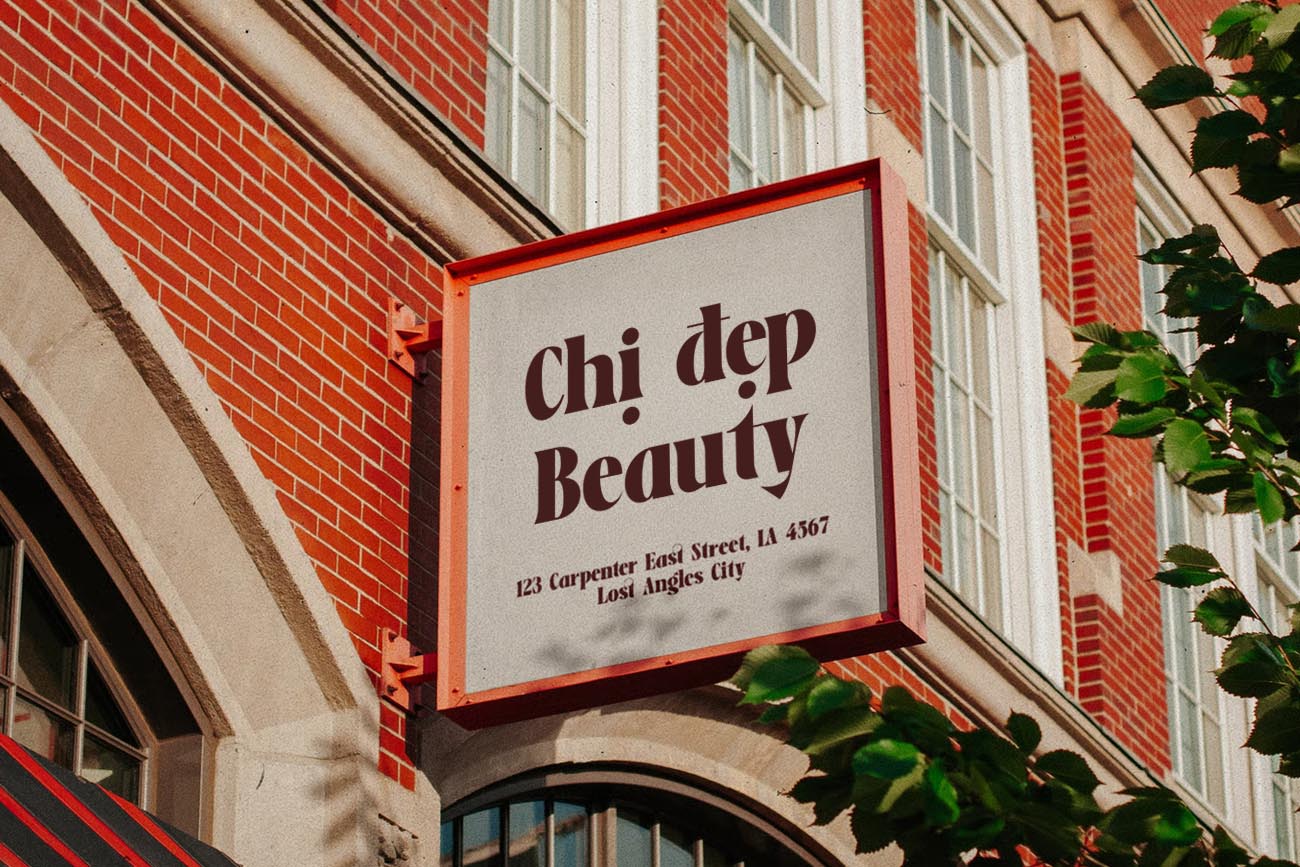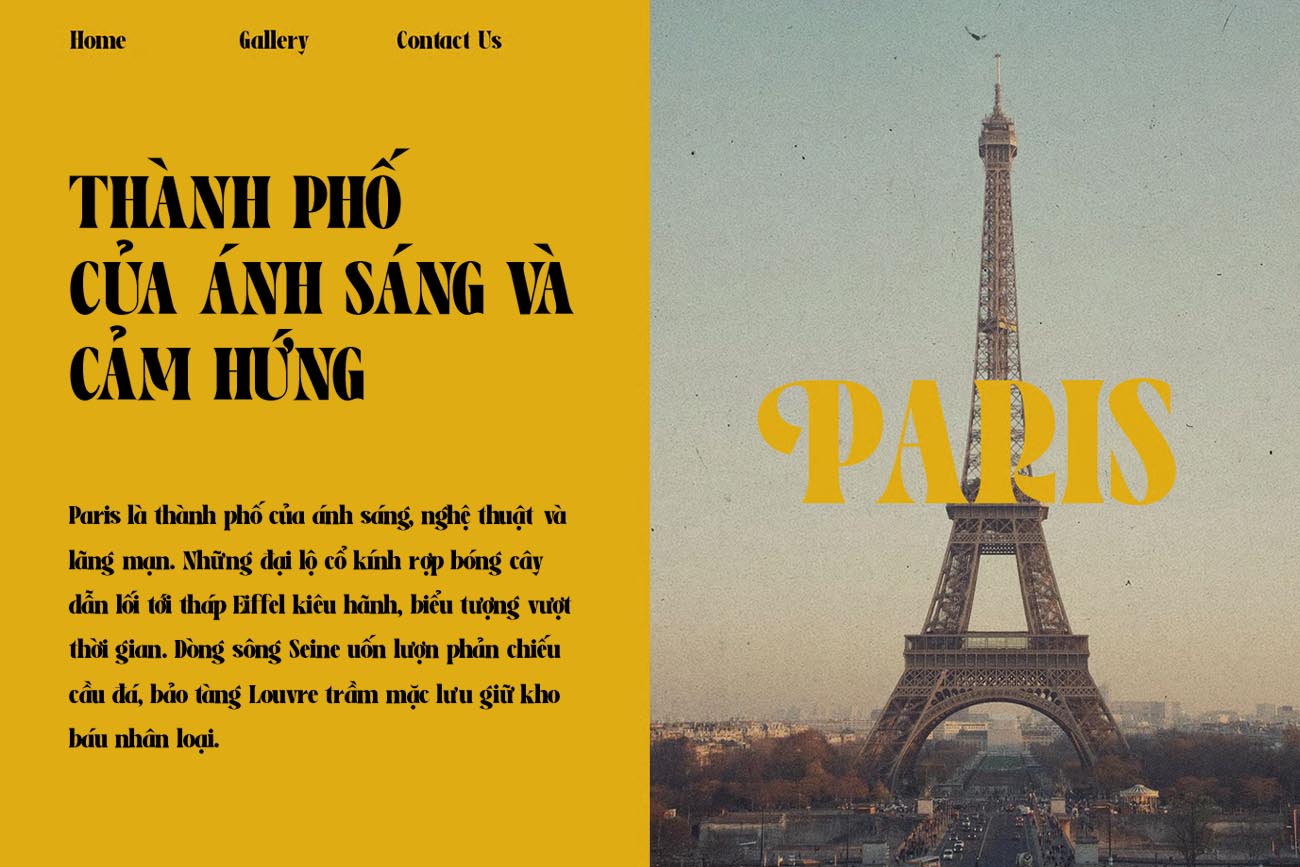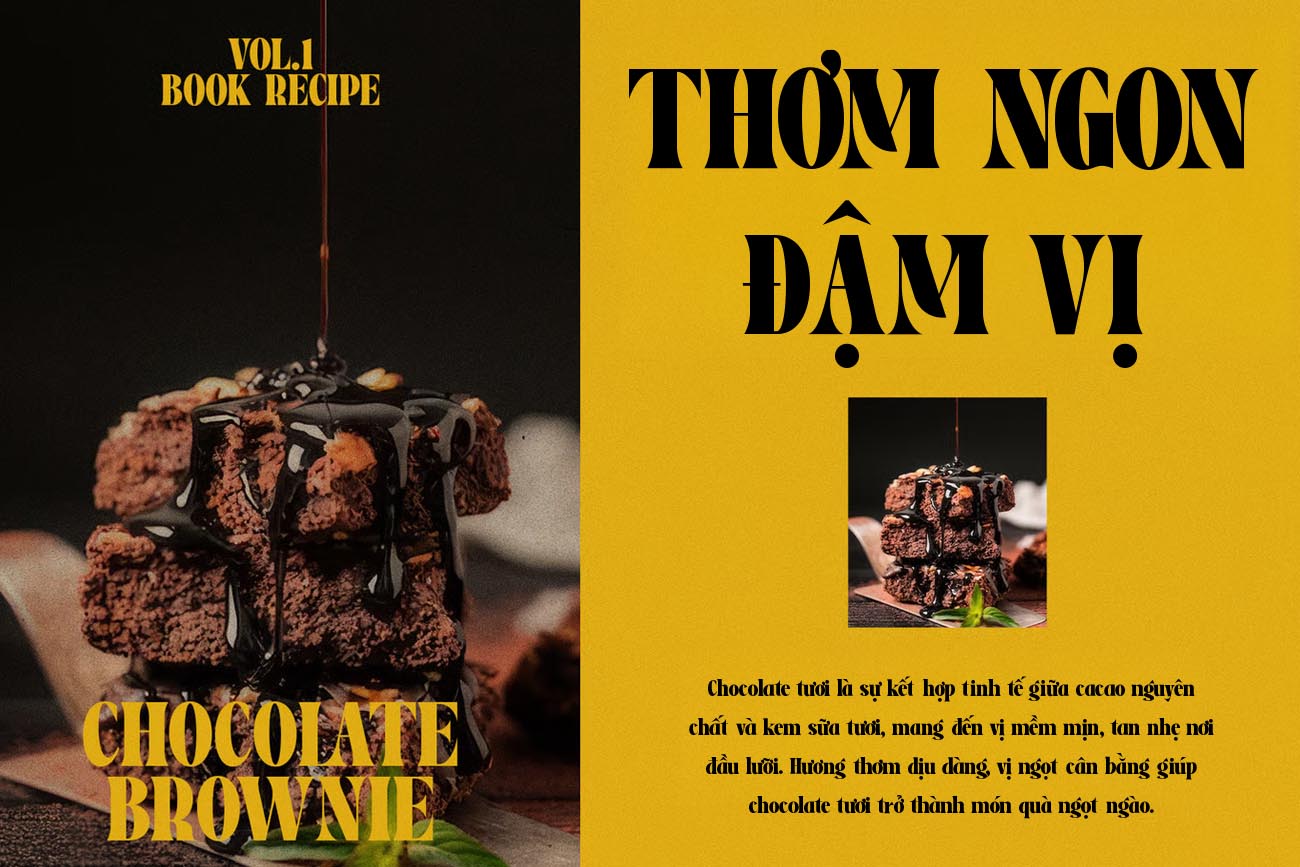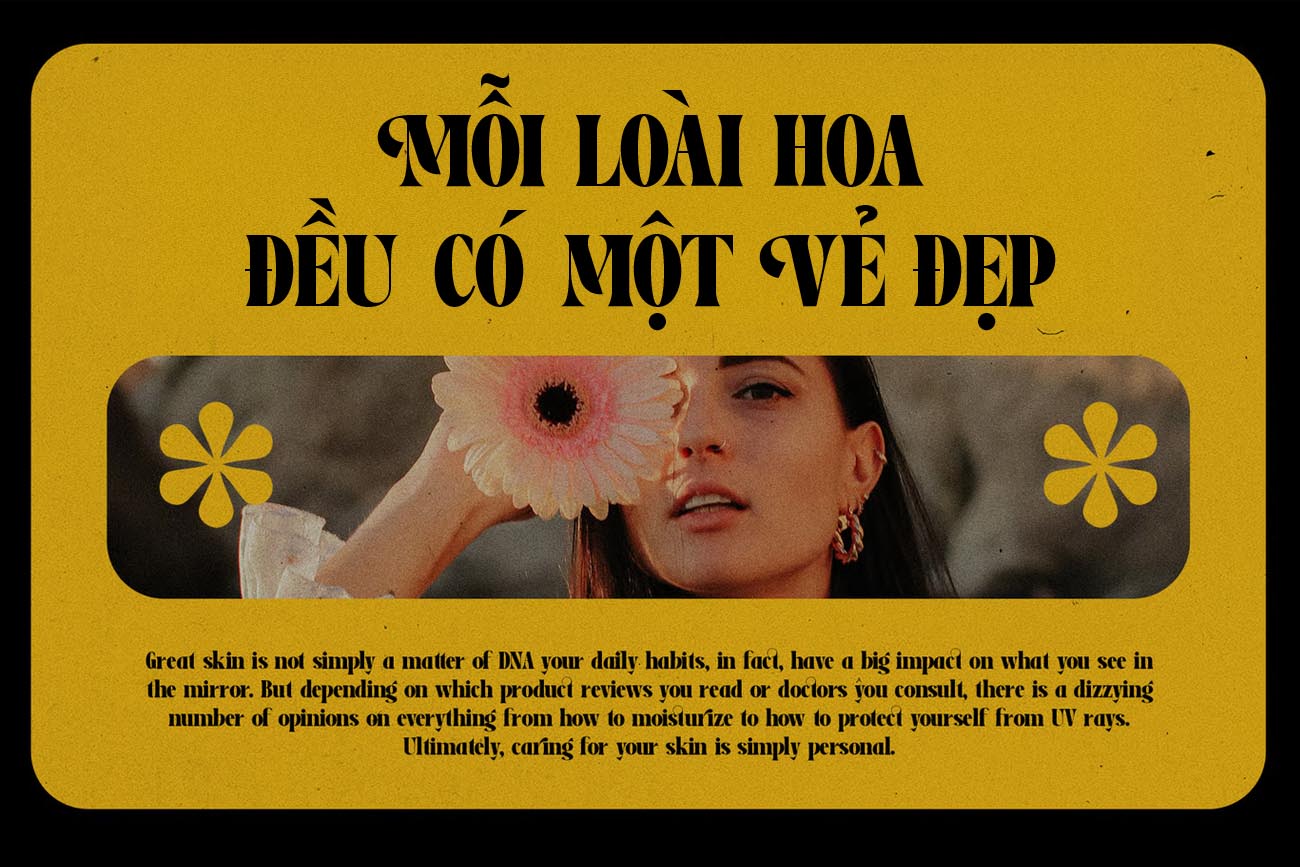
Font Việt hóa TH Romaben mang phong cách Vintage cổ điển
Trong thế giới thiết kế đồ họa, xu hướng tìm về những giá trị xưa cũ chưa bao giờ hết "hot". Những đường nét hoài cổ luôn mang lại cảm xúc mạnh mẽ và sự tin cậy cho người xem. Hôm nay, chúng tôi xin giới thiệu đến cộng đồng Designer bộ font Việt hóa TH Romaben – một lựa chọn hoàn hảo để thổi hồn vào các tác phẩm mang hơi hướng Retro.
Vẻ đẹp vượt thời gian của Romaben
Romaben là "đứa con tinh thần" của tác giả Rantau, một cái tên uy tín trong việc sáng tạo ra các bộ chữ mang phong cách Old Vintage. Đây là một mẫu font Serif (chữ có chân) sở hữu những đường nét gồ ghề có chủ đích, mô phỏng lại kỹ thuật in ấn trên giấy nhám của những thập kỷ trước.
Sự thu hút của Romaben nằm ở tính cách mạnh mẽ nhưng không kém phần tinh tế. Các nét thanh đậm được xử lý khéo léo, kết hợp với phần chân chữ (serif) vững chãi tạo nên một tổng thể vừa sang trọng, vừa bụi bặm.
Tại sao nên sử dụng bản Việt hóa TH Romaben?
Mặc dù bản gốc rất đẹp, nhưng rào cản ngôn ngữ thường khiến các Designer Việt gặp khó khăn khi xử lý văn bản tiếng Việt. Hiểu được điều này, team TH đã thực hiện chuyển ngữ và cho ra đời bộ font Việt hóa TH Romaben.
Điểm nổi bật của phiên bản này bao gồm:
1. Bộ dấu tiếng Việt chuẩn: Các dấu mũ, dấu thanh được vẽ lại tỉ mỉ, cân đối với chiều cao (x-height) của ký tự gốc, đảm bảo không bị chồng chéo khi gõ văn bản.
2. Tối ưu hóa hiển thị: Khoảng cách giữa các ký tự (kerning) được tinh chỉnh lại để phù hợp với thói quen đọc của người Việt.
3. Giữ nguyên tinh thần gốc: Mọi đặc trưng của dòng font Serif cổ điển từ bản Romaben gốc đều được bảo toàn trọn vẹn.
Ứng dụng trong thiết kế
TH Romaben cực kỳ phù hợp cho các dự án yêu cầu sự sang trọng và hoài niệm. Bạn có thể sử dụng bộ phông này cho:
•  Thiết kế Logo và nhận diện thương hiệu cho quán cà phê, tiệm đồ da, hoặc thời trang Vintage.
•  Làm tiêu đề (Headline) cho Poster, tạp chí hoặc bao bì sản phẩm.
•  Các thiết kế Typography trích dẫn hoặc bìa sách.